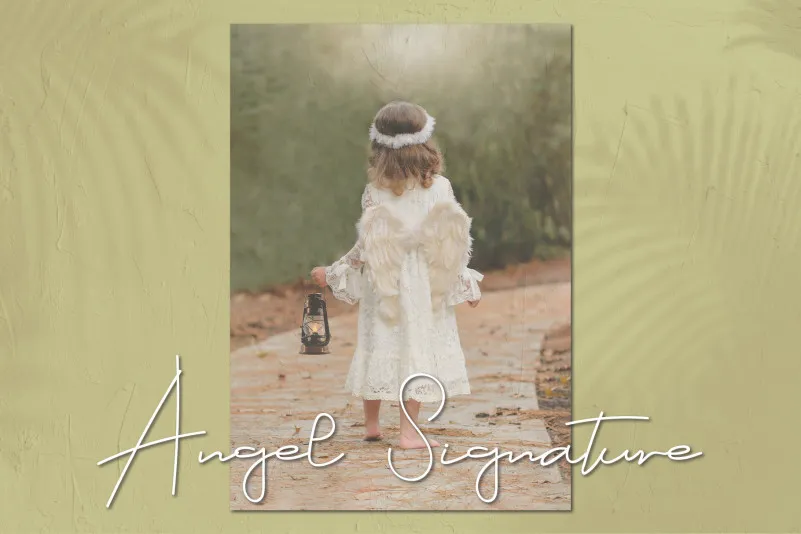
Angel Signature Font – Download Grátis
Esta é uma fonte escrita a mão fina e fluida, caracterizada por seu toque elegante, perfeita para seus projetos favoritos. Esta font suave vai se destacar em diversas ideias de design. Ela adicionará um toque alegre e romântico a cada projeto que você criar. Ideal para aqueles momentos especiais que querem deixar uma marca única. Agora, imagine usar esta fonte ‘Angel Signature Font’ de forma elegante em seu site, anúncio ou livro impresso; ela se destacará em qualquer formato, transmitindo sofisticação e romantismo sem perder a personalidade de cada letra. Aventure-se no mundo das fontes escritas a mão e descubra o poder de expressar sua identidade visual de uma forma única e emocionante.